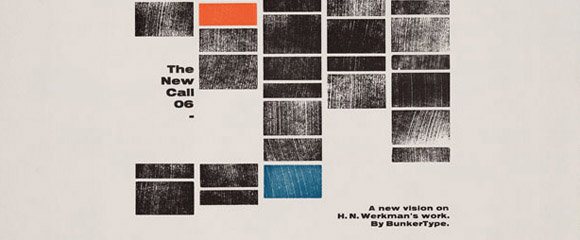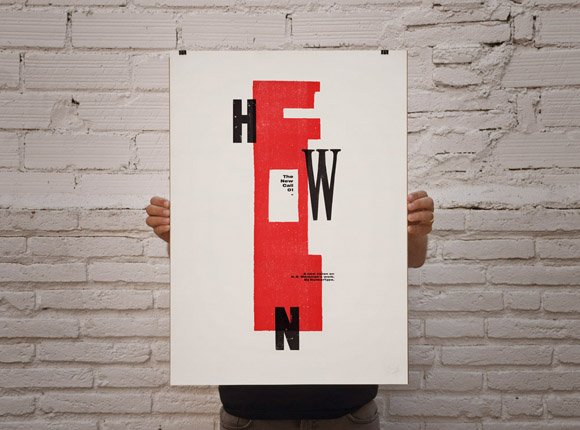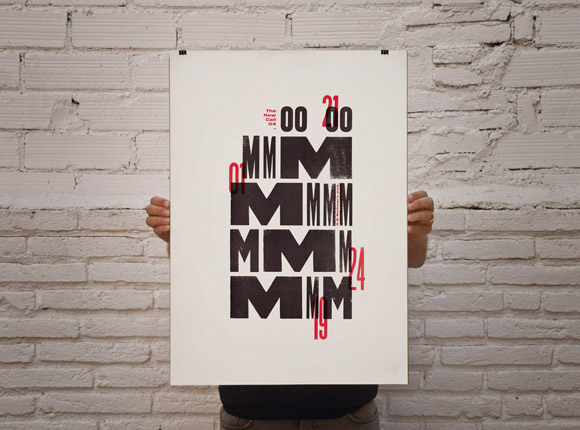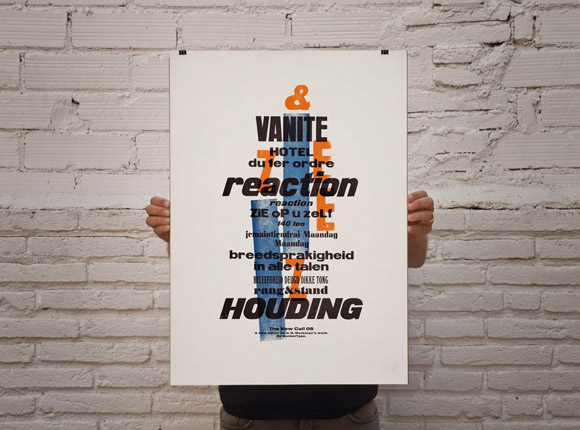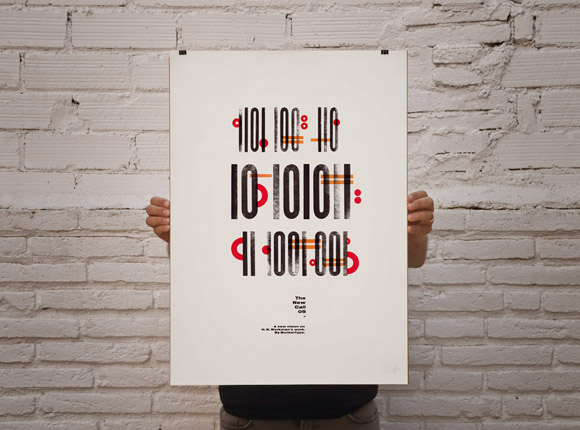
The Next Call fue una revista vanguardista publicada por el tipógrafo holandés Hendrik Nicolaas Werkman (1882-1945) durante los años 1923 a 1926. Un perfecto ejemplo de simbiosis entre arte vanguardista e imprenta clásica de la época de entreguerras. El impresor artesanal Jesús Morentin (Bunkertype) revisita la obra de Werkman con una segunda edición de carteles en los que nos muestra otra visión, en palabras del autor “más madura y personal” de la obra paradigmática del artista holandés.
Nos cuenta Jesús que: “Se trata de una colección que mantiene el mismo espíritu que el trabajo original -presentado en 2012- en el que cada composición se basaba en uno de los nueve números de la citada revista, pero en el que se ha trasladado el foco. Si en el primer acercamiento lo fundamental era el proceso y el aprendizaje, en “The New Call” he usado toda esa experiencia para poder centrarme en el resultado final, en la obra, ampliando notablemente la paleta de recursos cuando ha sido necesario, tanto en los aspectos técnicos como en los formales”.